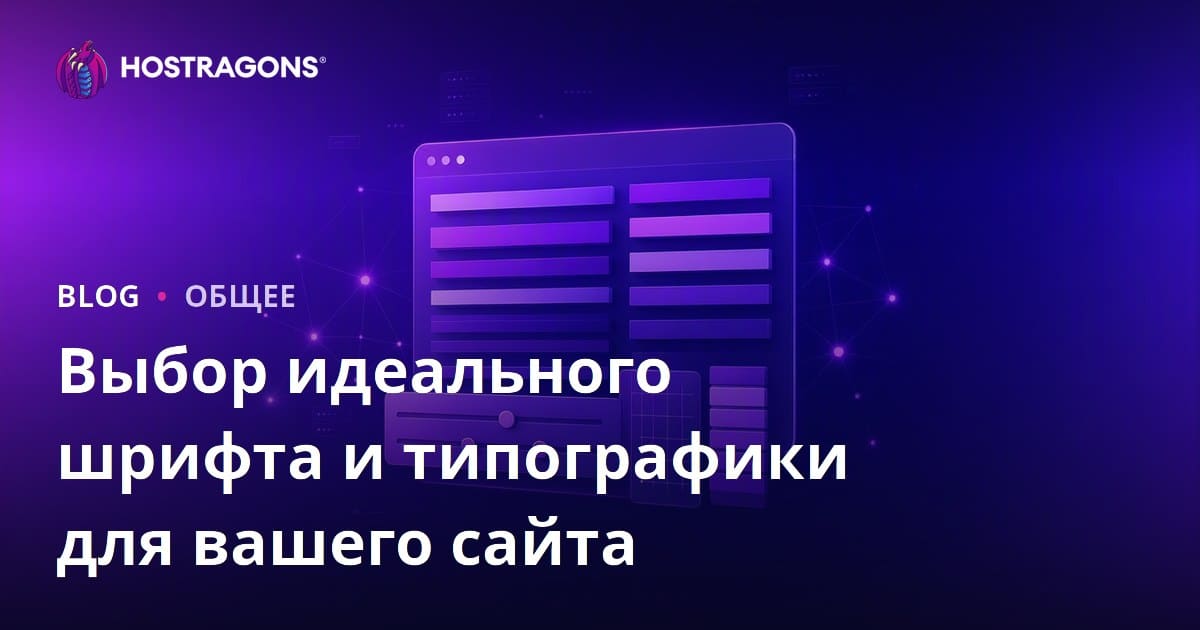
Выбор идеального шрифта и типографики для вашего сайта — важный элемент, который напрямую влияет на пользовательский опыт. В этом блоге рассматриваются основные принципы, на которые следует обращать внимание при выборе шрифтов для вашего сайта, а также то, как типографика может улучшить пользовательский опыт. Хотя предоставляется информация о различных типах шрифтов и функциях, рекомендуемые комбинации шрифтов и руководства по применению помогут вам создать наиболее подходящие стратегии типографики для вашего сайта. С эффективной типографикой для вашего сайта вы сможете привлечь посетителей и укрепить имидж бренда. Таким образом, ваш сайт станет более запоминающимся и удобным для пользователя.
Что стоит учитывать при выборе шрифтов для вашего сайта
Ваш сайт Выбор шрифта для Scott Séur — это не просто эстетический выбор, это важный элемент, который напрямую влияет на пользовательский опыт. Выбор правильного шрифта повышает читаемость, укрепляет вашу брендовую идентичность и дольше удерживает посетителей на сайте. Поэтому важно быть осторожным и принимать обоснованные решения при выборе шрифтов.
При выборе шрифта, прежде всего, ваша целевая аудитория Тебе стоит об этом подумать. Возраст, интересы и ожидания вашей целевой аудитории играют значительную роль в выборе типа и стиля шрифта. Например, если вы ориентируетесь на молодую и динамичную аудиторию, можно выбрать более современные и жирные шрифты. Однако если у вас сайт ориентирован на более традиционную и профессиональную аудиторию, будет уместнее использовать более классические и читаемые шрифты.
- Факторы, которые стоит учитывать при выборе шрифта
- Разборчивость: Шрифт легко читается при любом размере.
- Идентичность бренда: Шрифт отражает индивидуальность вашего бренда.
- Гармония: Сопоставление шрифта с общим дизайном вашего сайта.
- Разнообразие: Корректное отображение на разных устройствах и браузерах.
В таблице ниже вы можете найти примеры областей использования и особенностей различных типов шрифтов. В этой таблице показано, ваш сайт Это поможет вам выбрать наиболее подходящий для вас шрифт.
| Тип шрифта | Функции | Области применения |
|---|---|---|
| Шериф | Традиционный, формальный, читаемый | Названия, длинные блоки текста, академические публикации |
| Sans-Serif | Современный, минималистичный, чистый | Веб-сайты, мобильные приложения, короткие сообщения |
| Сценарий | Элегантный, личный, бросающий внимание | Логотипы, приглашения, специальные мероприятия |
| Дисплей | Смелый, оригинальный, декоративный | Заголовки, баннеры, реклама |
При выборе шрифта Комбинации шрифтов Также важно быть внимательным. Используя дополняющие и гармоничные шрифты, вы сможете сделать дизайн сайта более привлекательным и профессиональным. Используя другой шрифт для заголовков и другой шрифт для текста, вы можете создать визуальную иерархию и привлечь внимание пользователей. Помните, что выбор правильного шрифта ваш сайт Это может существенно повлиять на.
Способы улучшить пользовательский опыт с типографикой
На вашем сайте Одним из самых важных способов улучшить пользовательский опыт (UX) является использование эффективной типографики. Выбор правильного шрифта сочетает читаемость, иерархию и эстетические элементы, На вашем сайте Это может увеличить затраченное время и повысить коэффициенты конверсии. Типографика включает не только выбор шрифтов, но и такие факторы, как расположение текста, интервал между строками, кернинг и общая гармония дизайна.
Что такое типографика?
Типография, в самом простом определении, — это искусство визуального упорядочения текста. Эта схема направлена на улучшение читаемости, чёткую передачу сообщения и ваш сайт Он стремится внести вклад в его общий эстетичный облик. Хорошая типографика позволяет пользователям легко понимать содержание и На вашем сайте улучшает опыт просмотра.
Таблица ниже иллюстрирует ключевые компоненты типографики и их влияние на пользовательский опыт:
| Компонент | Объяснение | Влияние на пользовательский опыт |
|---|---|---|
| Выбор шрифта | Определение читаемых и подходящих шрифтов. | Это улучшает читаемость и укрепляет имидж бренда. |
| Размер и вес | Корректирую размеры и толщины текста. | Она создаёт иерархию, подчёркивает важную информацию. |
| Руководство | Редактирование пробела между строками. | Повышает читаемость и снижает утомляемость глаз. |
| Кернинг (трекинг) | Регулировка расстояния между персонажами. | Это влияет на читаемость, улучшает эстетический вид. |
Правильные типографические выборы, ваш сайт Удобно и впечатляет. Успешная стратегия типографики отражает личность вашего бренда и увеличивает взаимодействие с вашей целевой аудиторией.
Шаги, которые следует применять при типографике
- Поймите свою целевую аудиторию: Ваш выбор шрифта должен соответствовать ожиданиям вашей целевой аудитории.
- Отдайте приоритет читаемости: Убедитесь, что шрифт легко читается при любом размере.
- Отразите индивидуальность вашего бренда: Ваш шрифт должен отражать личность и ценности вашего бренда.
- Создайте иерархию: Поддерживайте чёткую иерархию между заголовками, подзаголовками и текстом.
- Обратите внимание на цвет и контраст: Убедитесь, что цвет шрифта обеспечивает достаточный контраст фону.
- Не забывайте о совместимости с мобильными устройствами: Убедитесь, что шрифт хорошо выглядит на разных устройствах и размерах экрана.
Влияние на пользовательский опыт
Влияние типографики на пользовательский опыт многогранно. Хорошая типографика, ваш сайт Это улучшает читаемость, облегчая понимание контента. В то же время он помогает пользователям быстро находить важную информацию, создавая визуальную иерархию. Неправильный выбор шрифта или плохо отредактированные тексты с вашего сайта Может привести к быстрому отслоюванию.
Следует отметить, что типографика — это не только эстетический элемент, но и элемент, который пользуются пользователями С вашим сайтом Это инструмент, который напрямую влияет на его взаимодействие. Следовательно, ваш сайт Выбор правильных шрифтов и внедрение эффективной типографики могут значительно улучшить пользовательский опыт.
Дизайн — это не только то, как он выглядит и ощущается. Дизайн — это то, как это работает. – Стив Джобс
На вашем сайте Последовательная типографика повышает узнаваемость бренда и формирует профессиональный имидж. Поэтому выбирайте типографику внимательно и ваш сайт Убедитесь, что он соответствует его общему дизайну.
Информация о различных типах шрифтов и их особенностях
Выбор правильного шрифта в веб-дизайне, ваш сайт Она имеет критическое значение с точки зрения эстетики и читаемости. Каждый тип шрифта позволяет передавать разные сообщения с уникальным характером и областями использования. Поэтому выбор правильного шрифта с учётом вашей целевой аудитории и цели сайта может существенно повлиять на пользовательский опыт.
В таблице ниже представлены общие характеристики и области использования различных типов шрифтов сравнительно. Это сравнение поможет вам выбрать наиболее подходящий шрифт для вашего проекта.
| Тип шрифта | Функции | Области применения | Примеры шрифтов |
|---|---|---|---|
| Шериф | С гвоздями, традиционные, формальные | Названия, длинные тексты, академические публикации | Times New Roman, Джорджия, Гарамонд |
| Санс Шариф | Без гвоздей, современно, просто | Веб-сайты, мобильные приложения, логотипы | Arial, Helvetica, Open Sans |
| Почерк | Весёлая, личная, привлекающая внимание | Титулы, приглашения, специальные проекты | Brush Script MT, Pacifico, Lobster |
| Дисплей | Ярко, оригинально, креативно | Логотипы, заголовки, плакаты | Импакт, Бебас Ной, Монсеррат |
Ещё одним важным фактором при выборе шрифта являются категории между типами шрифтов. Каждая категория имеет своё ощущение и назначение. Следовательно, ваш сайт Выбор правильной категории поможет вам точно отразить идентичность вашего бренда.
- Категории шрифтов
- Шрифты с засечками
- Шрифты без засечек
- Рукописные шрифты
- Моноширинные шрифты
- Шрифты для дисплея
Ниже вы найдёте более подробную информацию о некоторых часто используемых типах шрифтов и их особенностях. Эта информация упростит процесс выбора шрифта и ваш сайт Это поможет вам создать наиболее подходящую типографику для.
Шрифты с засечками
Шрифты с засечками характеризуются небольшими выступами (гвоздями) на концах букв. Они предлагают традиционный и формальный вид. Их часто предпочитают в печатных изданиях, таких как книги, газеты и академические издания, особенно потому, что они повышают читаемость длинных текстов. Их также можно использовать для заголовков или важного текста, который нужно выделить на сайтах.
Шрифты без засечек
Шрифты без засечек выглядят более современно, без кавычек. Благодаря чистым и простым линиям они обеспечивают лучшую читаемость на экране. Поэтому они идеально подходят для веб-сайтов, мобильных приложений и цифровых интерфейсов. Они также часто используются в логотипах и дизайне корпоративного стиля.
Рукописные шрифты
Рукописные шрифты — это шрифты, которые кажутся написаны от руки, вызывая более личную и интимную атмосферу. Их часто применяют в местах, где требуется внимание, например, в заголовках, приглашениях и специальных проектах. Однако их следует использовать с осторожностью, так как их читаемость в длинных текстах низкая. Рукописные шрифты, На вашем сайте Они могут быть эффективным инструментом для выделения определённой эмоции или стиля.
Выбор правильного шрифта играет важную роль в успехе вашего сайта. Обращайте внимание на выбор шрифтов, чтобы улучшить пользовательский опыт и точно отразить идентичность вашего бренда.
Рекомендуемые комбинации шрифтов и руководства по применению
Ваш сайт Поиск идеального сочетания шрифта как с точки зрения внешнего вида, так и для читаемости крайне важен. Правильное сочетание шрифтов отражает индивидуальность вашего бренда, а также увеличивает время, которое пользователи проводят на сайте. В этом разделе мы сосредоточимся на популярных и эффективных сочетаниях шрифтов и руководствах по их применению. Сочетание гармонии и контраста при выборе шрифта — один из ключей к профессиональному стилю.
| Основная купель | Вторичный шрифт | Область применения |
|---|---|---|
| Робото | Open Sans | Блог-посты, общие тексты |
| Монсеррат | Raleway | Заголовки, акцентный текст |
| Экспозиция Плейфэр | Монсеррат | Современные и стильные дизайны |
| Лато | Робото-плита | Корпоративные сайты |
При создании комбинаций шрифтов следует учитывать некоторые основные принципы. Во-первых, убедитесь, что ваш основной шрифт хорошо читается. Вторичный шрифт должен играть дополнительную роль к основному, используя его в заголовках, подзаголовках или текстах, которые требуют выделения. Также, На вашем сайте Также важно проверить лицензии используемых шрифтов и проверить, как они выглядят на разных устройствах. Так вы сможете предотвратить возможные проблемы, которые могут негативно повлиять на пользовательский опыт.
- Шаги создания комбинации шрифтов
- Определите идентичность своего бренда: Ваш выбор шрифта должен отражать индивидуальность вашего бренда.
- Выберите основной шрифт: Выберите шрифт, который читается и подходит для базового текста.
- Выберите вторичный шрифт: Определите шрифт, который совместим с вашим основным шрифтом и может использоваться для заголовков и выделений.
- Рассмотрим контраст: Убедитесь, что между весами шрифтов и стилями достаточно контраста.
- Тестируйте на разных устройствах: Проверьте, как шрифты отображаются на разных размерах экрана.
- Проверьте лицензии: Ознакомьтесь с правами на использование и лицензиями выбранных шрифтов.
Помните, что, на вашем сайте Типографика напрямую влияет на то, как пользователи взаимодействуют с вашим контентом. Выбор шрифта — это не только эстетический выбор, но и стратегическое решение для улучшения пользовательского опыта. Поэтому, тщательно выбирая комбинации шрифтов, ваш сайт Вы можете внести вклад в его общий успех.
Следующий отрывок подчёркивает важность выбора шрифта:
Типография — это не только расположение букв, но и искусство передачи духа и послания текста.
Стратегии и результаты типографики для вашего сайта
Ваш сайт Определение правильных стратегий типографики крайне важно не только для эстетики, но и для пользовательского опыта и имиджа бренда. Хорошая типографика улучшает читаемость вашего контента, дольше удерживает пользователей на сайте и помогает бренду создавать профессиональный имидж. К таким стратегиям относятся выбор шрифтов, размеры шрифтов, интервалы между строками, использование цвета и общие принципы дизайна. Успешная стратегия типографики может положительно повлиять на общую производительность вашего сайта.
При создании успешной стратегии типографики сначала следует учитывать свою целевой аудиторию и цель вашего сайта. Например, сайт, ориентированный на молодую аудиторию, может использовать более современные и динамичные шрифты, а сайт более формального учреждения предпочитает более классические и удобные для чтения шрифты. Кроме того, тип контента на вашем сайте также может влиять на выбор шрифта. Для длинных текстов предпочтительнее читать шрифты с засечками, тогда как шрифты без засечек могут быть более подходящими для заголовков и коротких текстов.
- Основные стратегии
- Определение целевой аудитории и цели сайта
- Выбор правильного семейства шрифтов (засечки, без засечек и т.д.)
- Оптимизировать размеры шрифтов и интервал между строками
- Правильная настройка цветового контраста
- Обеспечение мобильной совместимости
- Отражение индивидуальности бренда
В следующей таблице представлены возможные результаты различных типографических стратегий. Эти результаты можно оценивать по различным метрикам, таким как пользовательский опыт, восприятие бренда и коэффициенты конверсии.
| Стратегия типографии | Возможные результаты | Метрики измерения |
|---|---|---|
| Читаемый выбор шрифта | Повышение удовлетворённости пользователей, снижение коэффициента отскоков | Показатель отказов, время на странице |
| Точный цветовой контраст | Снижение напряжения глаз, улучшение доступности | Оценки доступности, отзывы пользователей |
| Мобильная совместимая конструкция | Лучший пользовательский опыт на мобильных устройствах, увеличение мобильного трафика | Скорость мобильного трафика, коэффициент мобильной конверсии |
| Шрифты, отражающие идентичность бренда | Сильное восприятие бренда, лояльность к бренду | Узнаваемость бренда, удовлетворённость клиентов |
ваш сайт При реализации типографических стратегий для S.A. следует применять подход непрерывного тестирования и оптимизации. Проводя A/B-тесты, вы можете экспериментировать с разными сочетаниями шрифтов, размерами шрифтов и цветовыми схемами, чтобы определить, какие комбинации дают наилучшие результаты. Помните, что типографика — это не только элемент дизайна, но и пользовательский опыт и Успех бренда Это критически важный фактор, который напрямую влияет на него.
Часто задаваемые вопросы
На что стоит обратить внимание при выборе шрифта для моего сайта? Это читаемость, внешний вид или другие факторы?
При выборе шрифтов для сайта следует учитывать такие факторы, как читаемость, идентичность вашего бренда и целевая аудитория. Читаемость всегда должна быть приоритетом, но эстетика шрифта также должна отражать имидж вашего бренда и положительно влиять на время, которое посетители проводят на вашем сайте. Также важно, чтобы шрифт соответствовал общему дизайну вашего сайта.
Каково влияние типографики на пользовательский опыт и как я могу его измерить?
Типографика напрямую влияет на пользовательский опыт. Хорошая типографика облегчает чтение, делает информацию более понятной и улучшает общую эстетику сайта. Для измерения этого эффекта вы можете изучить такие показатели, как коэффициент отказов, время пребывания на объекте, коэффициенты конверсии, провести A/B-тесты и оценить отзывы пользователей.
В чём основные различия между шрифтами serif, sans-serif и другими типами шрифтов, и какой из них больше подходит для моего сайта?
Шрифты с засечками имеют цитируемые символы, а шрифты без засечек — без цитировок. Шрифты с засечками часто имеют традиционный и формальный стиль, тогда как шрифты без засечек предлагают более современный и минималистичный вид. Какой тип больше подходит, зависит от содержания сайта, идентичности бренда и целевой аудитории. Обычно используется Sans-serif для заголовков и Serif для текстовых тел.
Можете привести примеры комплементарных комбинаций шрифтов, которые я могу использовать на своём сайте?
Да, некоторые комбинации шрифтов, которые дополняют друг друга: Open Sans (Sans-serif) для заголовков и Montserrat (Sans-serif) для текстовых тел; Roboto (Sans-serif) для заголовков и Merriweather (Serif) для текстовых тел; Playfair Display (Serif) для титров и Montserrat (без засечек) для текстовых корпусов. Это лишь несколько примеров, и вы можете попробовать разные комбинации в зависимости от стиля и содержания вашего сайта.
Какие шаги мне следует следовать при создании стратегии типографики моего сайта?
При создании типографики для вашего сайта сначала необходимо определить свою целевую аудиторию и идентичность бренда. Затем следует выбрать подходящие шрифты, учитывая такие факторы, как читаемость, доступность и совместимость. Вам следует улучшить пользовательский опыт, оптимизируя такие детали, как размеры шрифтов, интервалы между строками и интервалы между буквами. Наконец, регулярно тестируйте и совершенствуйте свою стратегию.
Как мне правильно регулировать размер и расстояние между строками шрифтов на моём сайте, чтобы обеспечить наилучший опыт чтения?
Вам следует корректировать размер шрифта, учитывая такие факторы, как возраст и зрение вашей целевой аудитории. В целом, для текстовых тел рекомендуется размер шрифта 16 пикселей и больше. Высота строки обычно должна быть от 1,4 до 1,6 размера шрифта. Таким образом, тексты читаются легче, а усталость глаз снижается. Также важно устанавливать разные размеры шрифтов и интервалы между строками для мобильных устройств.
Каковы преимущества и недостатки использования бесплатных ресурсов шрифтов, таких как Google Fonts?
Преимущества бесплатных ресурсов по шрифтам, таких как Google Fonts, включают широкий выбор шрифтов, легкую интеграцию и часто оптимизацию для производительности. Недостатки заключаются в том, что некоторые шрифты могут снижать оригинальность вашего сайта из-за широкого распространения и, в редких случаях, приводить к проблемам с производительностью. Кроме того, некоторые специализированные шрифты могут быть недоступны бесплатно.
Как оптимизировать шрифты, чтобы они не влияли на производительность моего сайта?